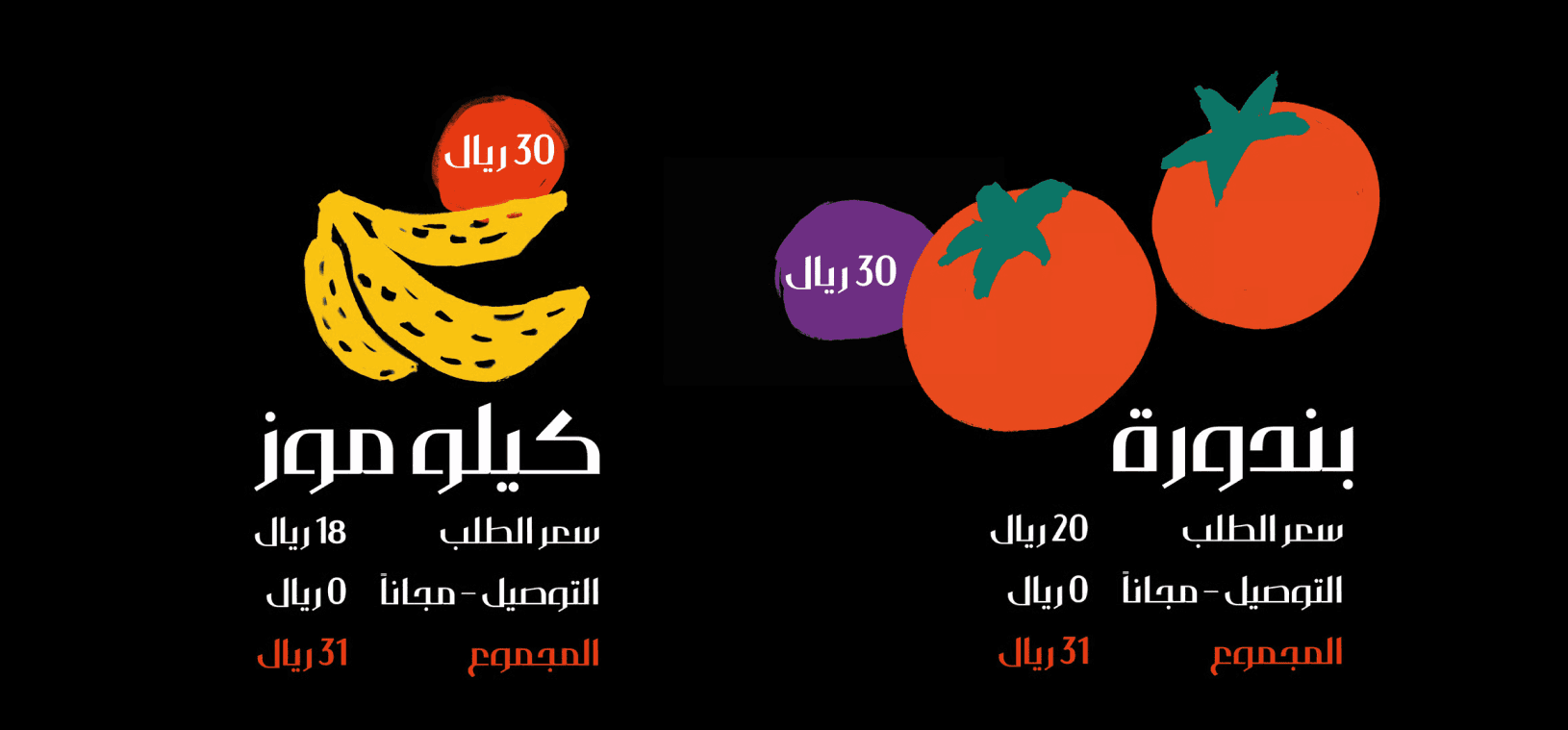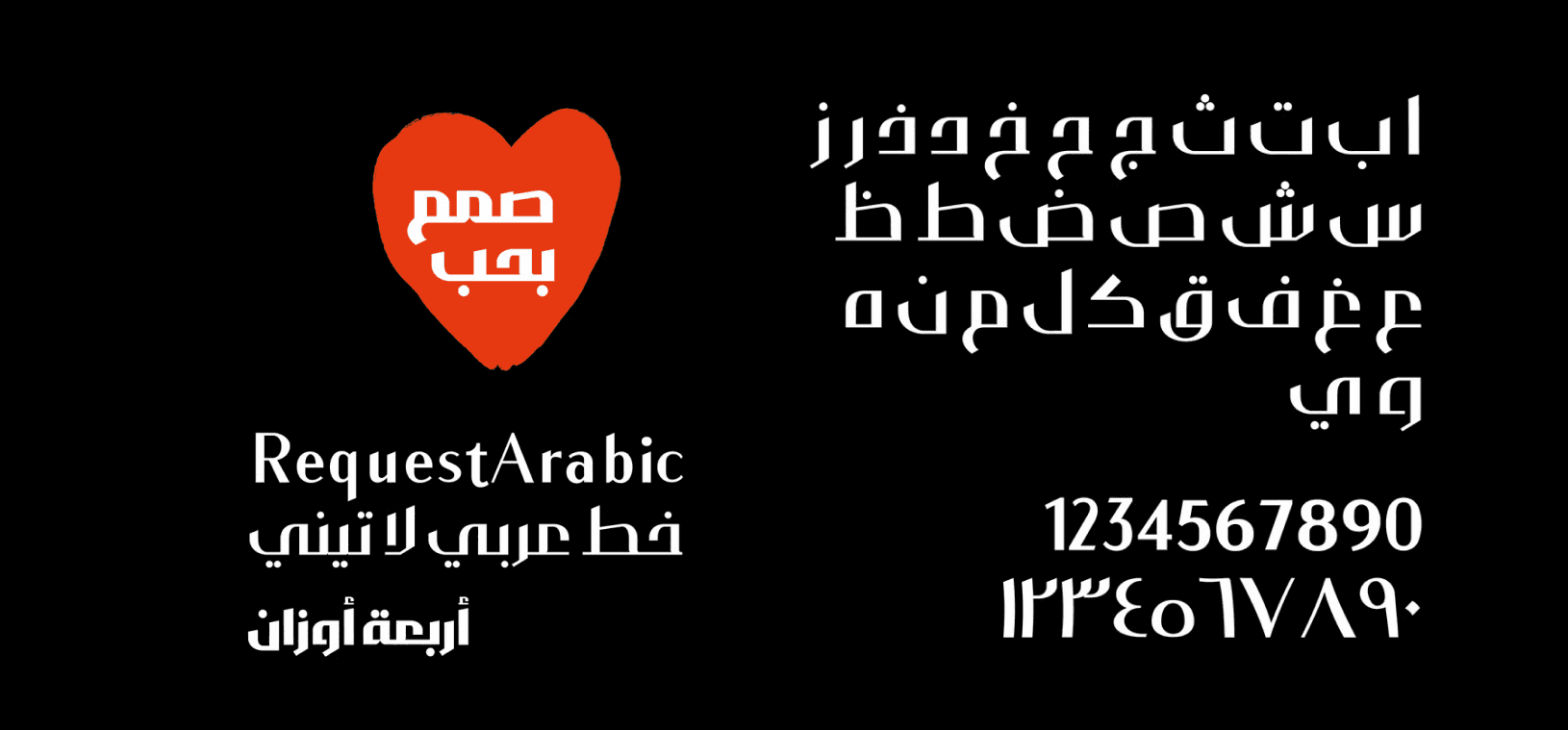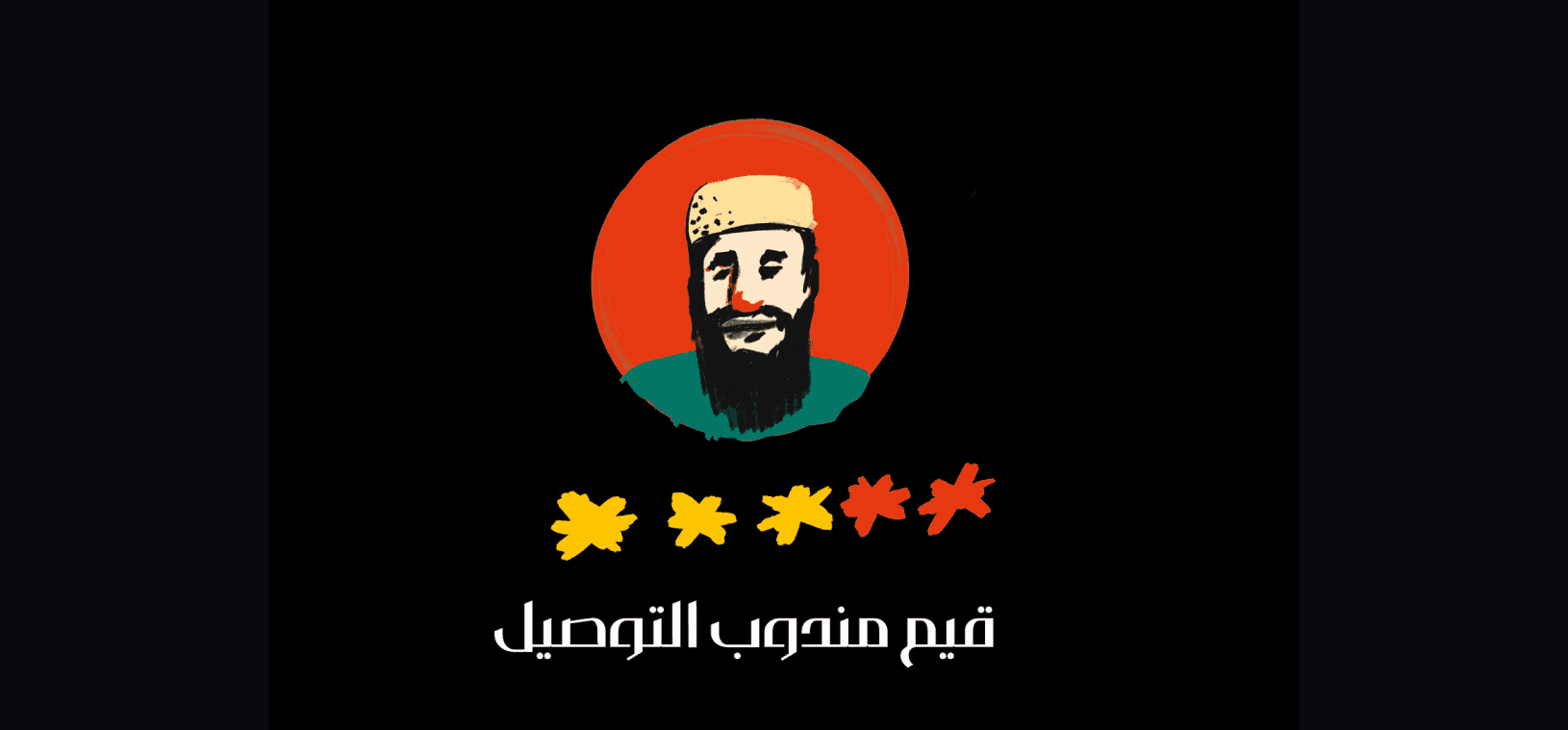
يتميّز خط ريكويست بتصميم عصري أنيق يأتي بأربعة أوزان متكاملة يمكن استخدامها معًا بتناغم سلس. يتضمن الخط مجموعة غنية من التراكيب والربطات (ligatures) التي تمنح النصوص مظهرًا احترافيًا ومتميزًا. مثالي للتصميمات الإعلانية، والطباعة التحريرية، والعلامات التجارية التي تبحث عن شخصية بصرية واضحة وقوية.